Декоративный шрифт для музыкального проекта: как выбрать
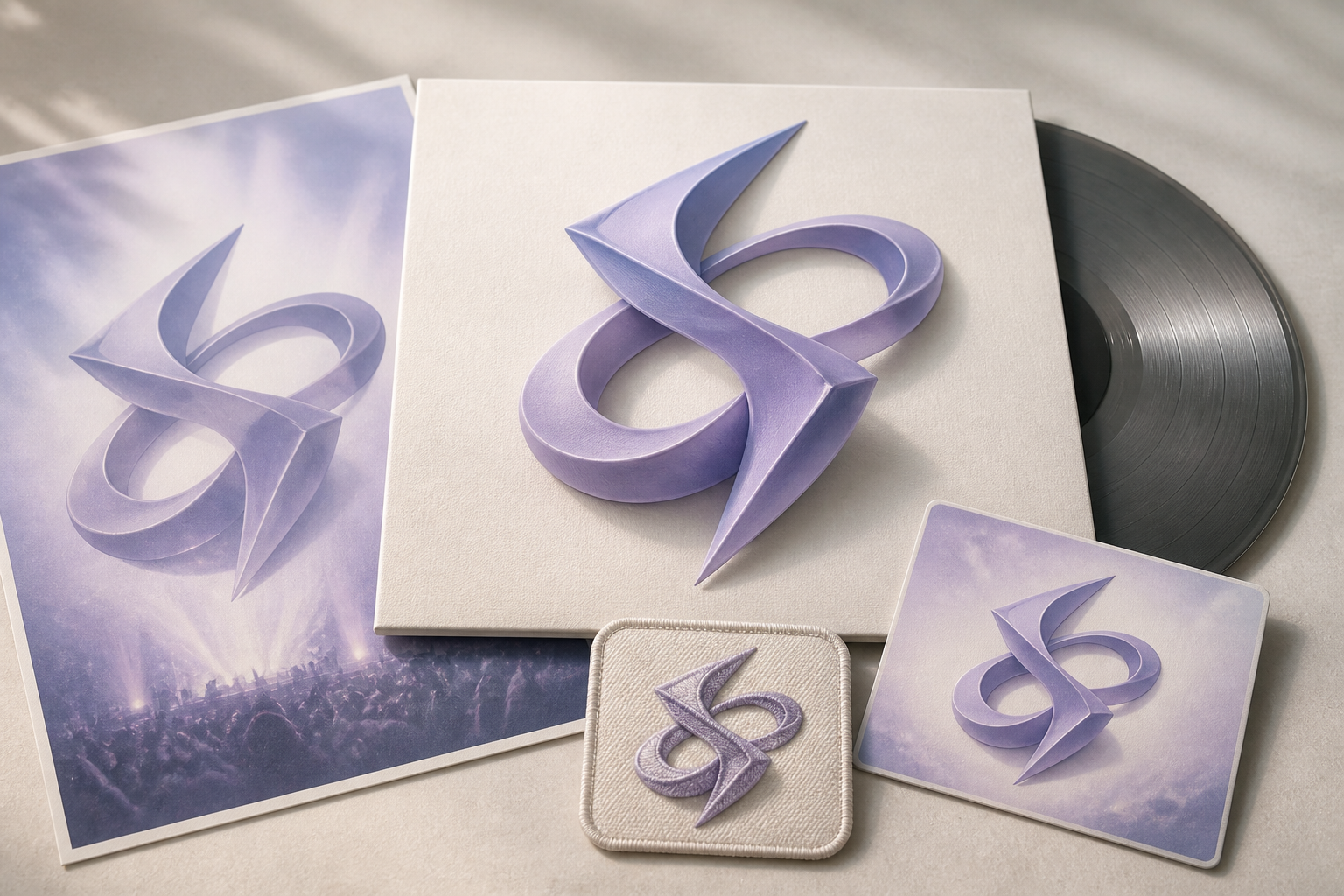
Декоративный шрифт для музыкального проекта выбирают не только по внешней выразительности, но и по соответствию жанру, аудитории, носителям и требованиям к читаемости. Удачное решение помогает создать узнаваемый образ группы или артиста, а грамотная типографическая система сохраняет его на обложке, афише, сайте, мерче и в социальных сетях.
Почему шрифт становится частью музыкального образа
В музыкальном брендинге шрифт работает как визуальный эквивалент звучания. Острые углы, плотные формы и резкий контраст могут поддержать эстетику металла или хардкора; мягкая пластика и необычный ритм букв уместны для инди-проекта; геометричная гротескная конструкция может передавать электронную, клубную или футуристическую направленность. Это не буквальный перевод жанра в графику, а способ сформировать ожидаемое настроение ещё до прослушивания трека.
Название музыкального проекта часто видят раньше, чем слышат его музыку: на превью стриминга, постере, аватаре или обложке сингла. Поэтому типографика должна одновременно привлекать внимание и помогать быстро распознать имя. Если декоративность полностью разрушает форму слова, визуальный эффект становится помехой для запоминания.
Сначала определите характер проекта, а не стиль шрифта
До просмотра каталогов сформулируйте несколько характеристик проекта: жанр, эмоциональный диапазон, сценический образ, ценовой сегмент мерча и тип аудитории. Один и тот же шрифт может выглядеть убедительно в названии панк-группы, но неуместно в брендинге камерного электронного дуэта. Важно учитывать не только музыку, но и то, как артист говорит, выглядит и взаимодействует со слушателями.
- Опишите проект тремя или четырьмя прилагательными: например, «холодный, минималистичный, ночной».
- Определите, нужен ли образ агрессивный, загадочный, романтичный, ироничный или технологичный.
- Решите, должна ли айдентика выглядеть актуально несколько лет или намеренно ссылаться на конкретную эпоху.
- Соберите примеры визуальных ассоциаций: концертный свет, аналоговая техника, клубная сцена, рукописные плакаты или цифровые интерфейсы.
Практический пример: для построк-трио с атмосферным звучанием чрезмерно агрессивный blackletter может создать ожидание экстремальной музыки и исказить позиционирование. Более точным решением станет контрастный шрифт с нестандартными пропорциями, который сохраняет напряжение, но оставляет в образе пространство и меланхолию.
Критерий 1. Соответствие жанру и сценической эстетике
Жанр задаёт направление поиска, но не должен превращаться в шаблон. Для рэп-проекта могут подойти массивные дисплейные формы, грубая фактура или нарочито сжатые буквы. Для джазового коллектива — выразительная антиква, ретро-гротеск или каллиграфический акцент. Для поп-исполнителя — пластичный шрифт с узнаваемой деталью, который хорошо масштабируется в цифровых форматах.
Проверяйте, не повторяет ли выбранная стилистика слишком очевидный визуальный код конкурентов. Если все проекты в нише используют одинаковые готические буквы, индивидуальность можно построить на другой характеристике: необычной ширине, асимметрии, ритме межбуквенных интервалов или специальной обработке одной буквы в названии.
Критерий 2. Читаемость на разных размерах
Декоративный шрифт особенно часто теряет читаемость при уменьшении. Тонкие линии исчезают, сложные контуры сливаются, а тесные интервалы превращают слово в пятно. Поэтому тестировать гарнитуру нужно не только на большой обложке, но и в размере аватара, карточки трека, мобильного баннера и маленькой наклейки на упаковке.
- Наберите название проекта в одну строку и уменьшите его до размера аватара.
- Проверьте чтение на светлом и тёмном фоне.
- Оцените слово в монохромном варианте без свечения, тени и текстуры.
- Посмотрите, различаются ли соседние буквы и не образуются ли случайные провалы между ними.
- Попросите человека, который не знаком с проектом, прочитать название без подсказки.
Критерий 3. Поддержка кириллицы и нужных символов
Для русскоязычного музыкального проекта наличие кириллицы критично. Даже если логотип будет написан латиницей, в коммуникациях появятся названия треков, даты концертов, описания релизов и подписи к публикациям. Гарнитура без полноценной кириллической версии заставит смешивать разные шрифты, и визуальная система быстро потеряет цельность.
Проверьте не только русский алфавит, но и буквы, которые часто вызывают проблемы в декоративных гарнитурах: Д, Л, Ж, Ф, Ы, Й, Ц, Щ и прописные формы. Отдельно протестируйте цифры, дефис, кавычки, знак номера, скобки и валютные символы. Для афиш и анонсов эти знаки так же важны, как сами буквы.
Критерий 4. Набор начертаний и типографическая система
Декоративная гарнитура редко подходит для всего текста. Её разумно использовать в логотипе, заголовках, названиях релизов или коротких акцентах, а для описаний и навигации выбрать нейтральный текстовый шрифт. Такое сочетание создаёт иерархию: выразительная гарнитура отвечает за характер, а спокойная — за удобство чтения.
Хороший декоративный шрифт для музыкального проекта соединяет характер, узнаваемость и практичность. Оценивайте не только настроение букв, но и кириллицу, читаемость, носители, сочетания и лицензию. Такой выбор помогает построить целостную типографику, которая поддерживает музыку, а не отвлекает от неё.